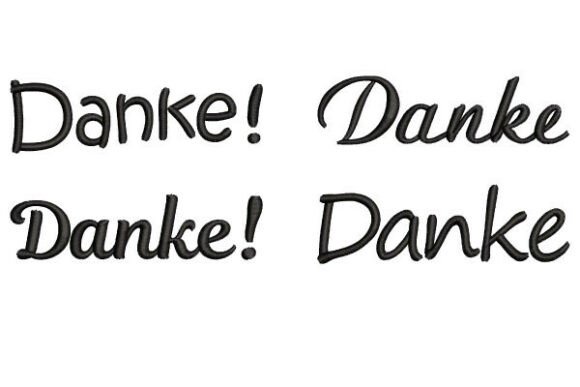
Danke German Lettering
適切なデザイン要素を見つけるのは難しい場合がありますが、Danke German Letteringは作品を即座に引き立てる優れたコレクションを提供します。
POD(オンデマンド印刷)製品、結婚式の招待状、またはソーシャルメディアのグラフィックを作成している場合でも、Danke German Letteringは理想的です。